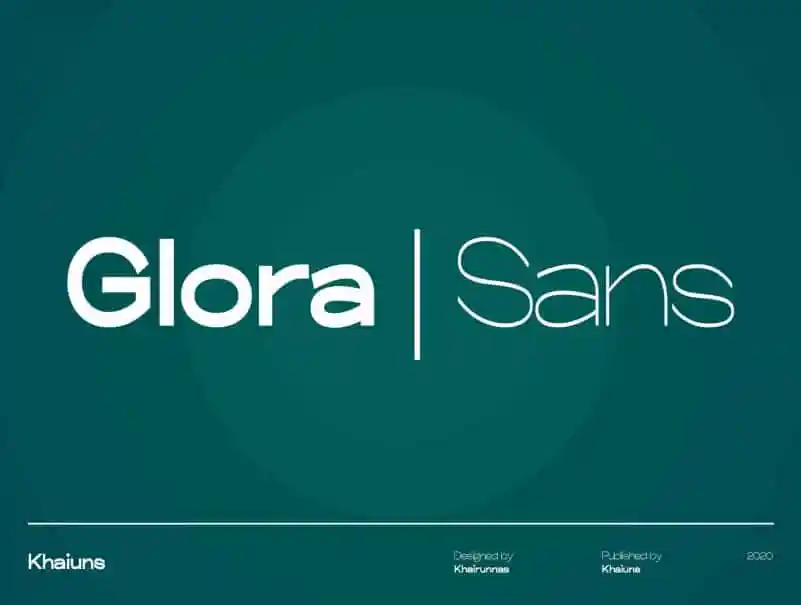
Glora Sans Serif Font – Download Grátis
A Glora Sans Serif Font é uma tipografia simplista e elegante que se destaca por sua versatilidade em qualquer tamanho. Criada pelo designer khaiuns no site 99designs, essa fonte moderna sem traço traz um toque suave e eficaz para projetos variados. Com letras maiúsculas e minúsculas fortes que se destacam em uma ampla gama de aplicações, a Glora é perfeita para trabalhos digitais ou impressos. Seu design jovial e moderno torna-a uma excelente opção para aqueles buscando um visual contemporâneo e minimalista em seus projetos. A Glora não apenas preza pela simplicidade, mas também pela eficácia no design gráfico, tornando-a uma fonte que merece atenção entre as sans serif disponíveis atualmente.